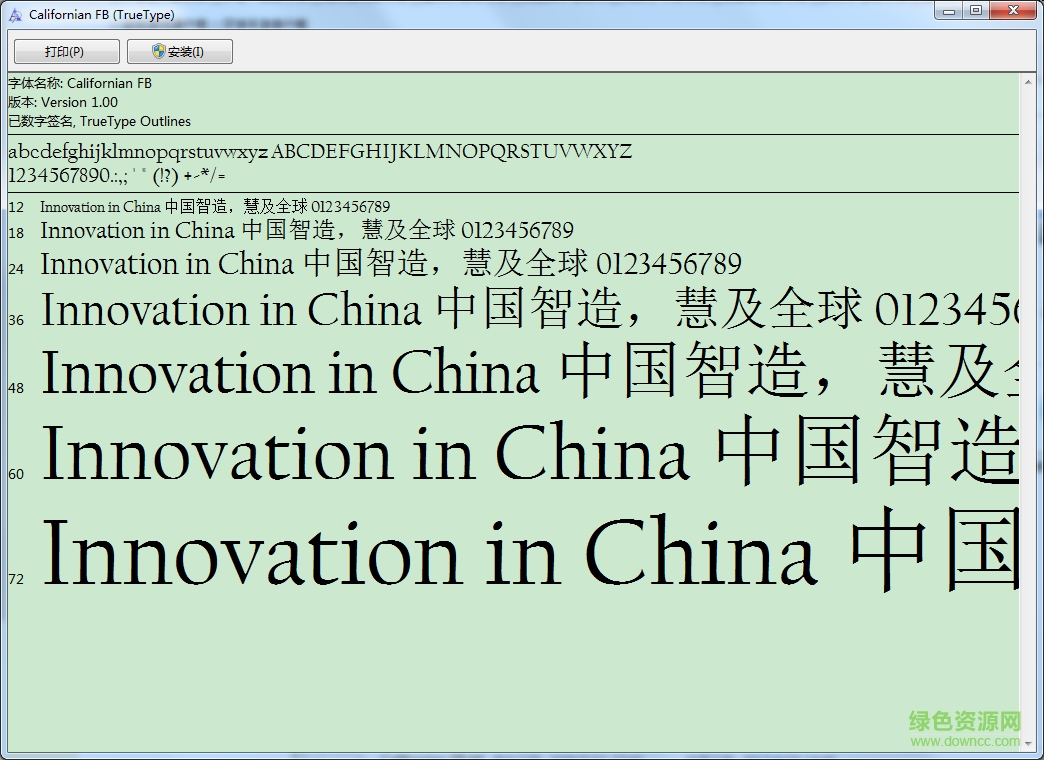
CalifornianFB字體
CalifornianFB是一款端正大氣的英文字體,該字體結(jié)構(gòu)簡(jiǎn)潔,線條剛硬,整體效果非常出眾,廣泛的應(yīng)用于封面設(shè)計(jì)、廣告設(shè)計(jì)、排版印刷等領(lǐng)域,喜歡的朋友歡迎來綠色資源網(wǎng)下載!